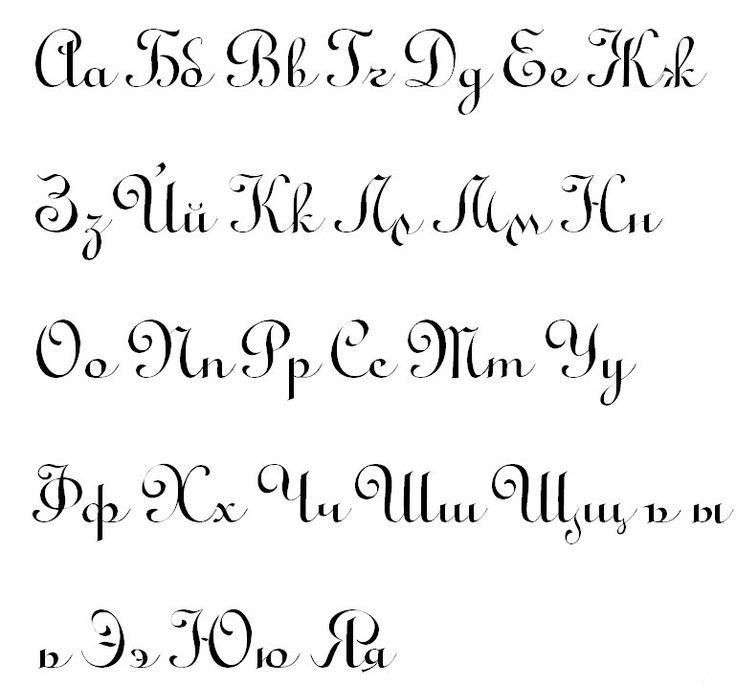
Шрифты буквы для оформления: Шрифты для ников онлайн, красивые буквы
Зачем нужно изменение шрифта на сайте
Казалось бы, все итак выглядит отлично. Однако, в бесконечном потоке статей и публикаций, пользователь просто вас не заметит. Это абсолютно не подходит тем, кто хочет привлечь внимание: блогерам, мастерам, предоставляющим услуги, или бизнесменам. Распространенность популярности товара или контента напрямую зависит от того, как вы сможете привлечь новых пользователей. С обычными шрифтами у вас ничего не выйдет.
В постах пользователь двигается следующим образом:
- Просмотр картинки. Если она его заинтересует, то он перейдет к тексту.
- Чтение поста, что подразумевается под картинкой или что хочет сказать автор.
- Просмотр профиля автора или его канала.
Если картинку можно легко сделать в фотошопе, то с постами все значительно сложнее. В том же Инстаграм, они представляют собой бесформенное нечто, которое разве что можно выделить смайлами. Мы же предоставляем совершенно иной подход.
Как написать фразу красивым шрифтом
Красивые шрифты, символы, буквы для оформления имён, ников, профилей.
Красивые и крутые символы — набор значков, букв, закорючек и смайликов для оформления различных текстовых кусочков или отдельных слов. Принцип оформления текста, основан на замене стандартных букв необычными символами, которые напоминают по форме исходные. Второй способ, симметричное добавление по краям текста красивых символов.
Наиболее популярными элементами для оформления сейчас являются: ники для игр, псевдонимы, имена для соцсетей, статусы, профили Instagram, описания каналов Telegram или Tiktok. В дополнение, некоторые пользователи используют красивые символы на аватарках или фотографиях.
Waverly
Шрифт Waverly вдохновлен эпохой ар-деко – современный и футуристический, с подчеркнутыми заостренными чертами.
Дизайнер Коннари Фейген (Connary Fagen) сделал для Waverly шрифт, состоящий из заглавных букв, который нам нравится.
Canciller
Мануэль Коррадайн и Серхио Рамирес разработали этот элегантный стильный шрифт.
Шрифт представляет собой сочетание красивой каллиграфии с удобочитаемостью типографики.
Этот шрифт можно использовать для самых разных проектов «сделай сам» и домашнего декора.
Sancreek
Шрифт Sancreek очень похож на Saloon.![]()